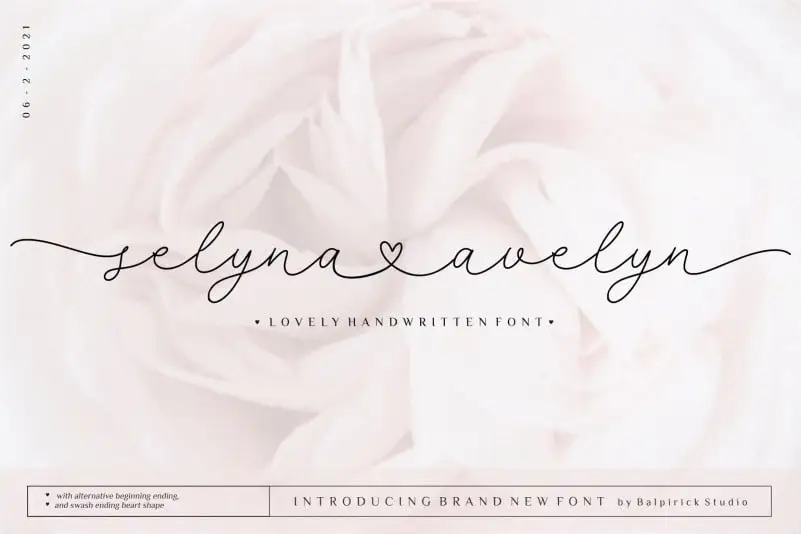
Selyna Avelyn Script Font – Fonte Grátis
Selyna Avelyn Script Font
A fonte Selyna Avelyn é uma elegante escolha para projetos que valorizam a sofisticação e a criatividade na tipografia. Perfeita tanto para aplicar em pacotes de produtos, criação de marcas ou publicações de revistas, ela também se destaca no design social de mídias como redes sociais, tornando suas letras ainda mais vibrantes e atemporais. Sua versatilidade se estende até eventos especiais como casamentos, onde sua textura fluida e arredondada enriquece a decoração e o estilo do evento. Além disso, é uma fonte ótima para expressar mensagens importantes ou artigos de conteúdo relevante em um background mais minimalista. A fonte Selyna Avelyn está projetada para se destacar, seja nos detalhes pequenos das embalagens até as grandes aparições no centro da página. Suas linhas fluidas e suas formas delicadas criam uma atmosfera encantadora que combina perfeitamente com a estética de balpirick. Seja você um designer em busca de criar um projeto memorável, ou simplesmente alguém que quer expressar sua mensagem através de fontes diferentes, Selyna Avelyn é uma excelente escolha. Suas linhas delicadas e suas formas fluidas garantem uma experiência visual harmoniosa, seja o seu próximo projeto gráfico ou a reviravolta em um design existente.